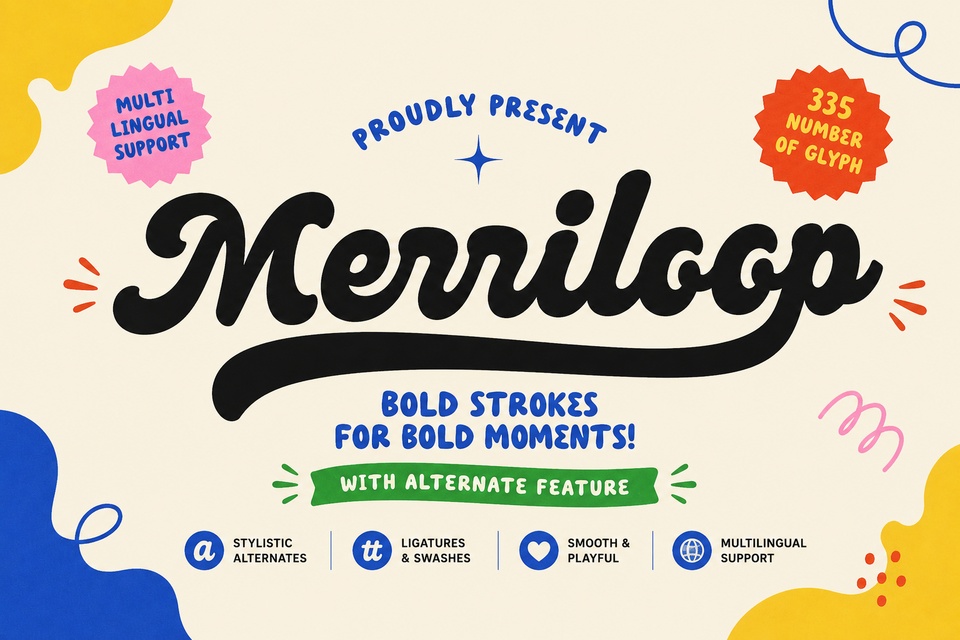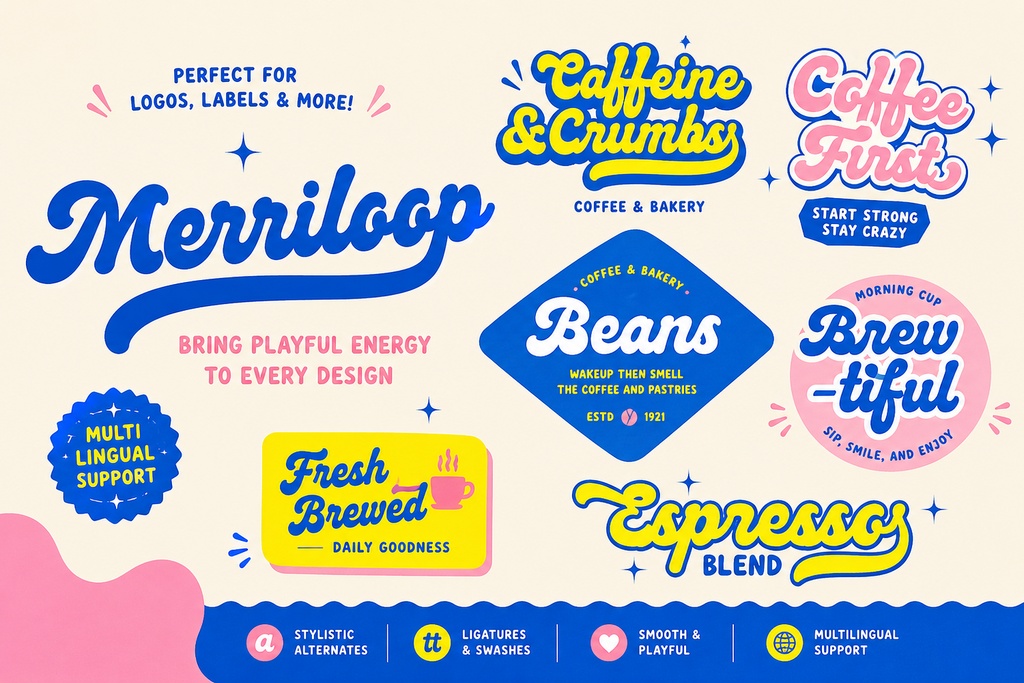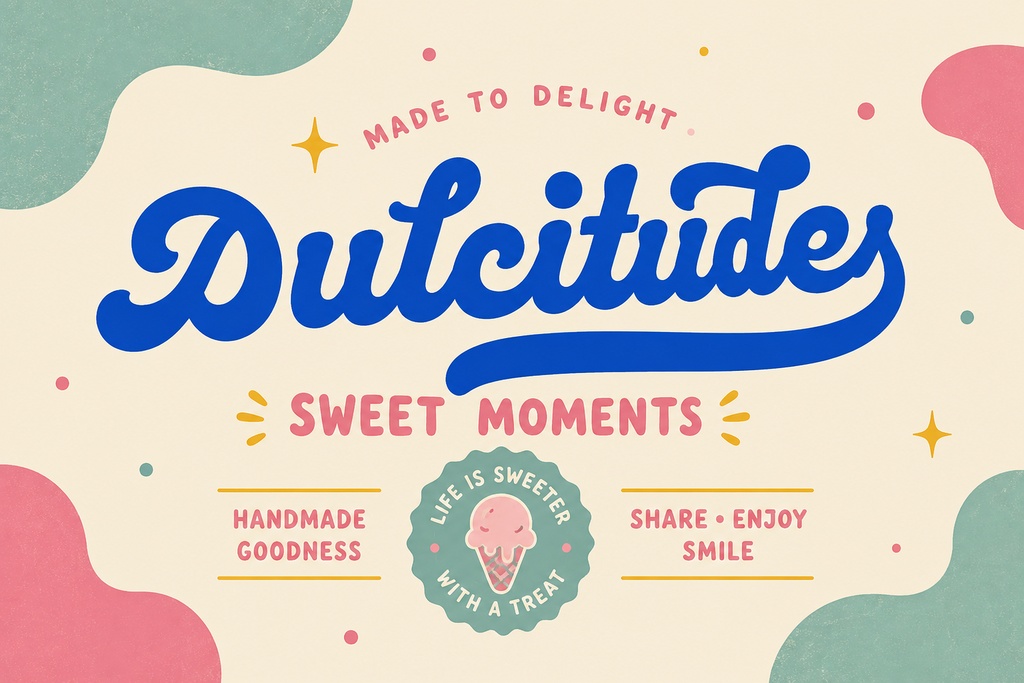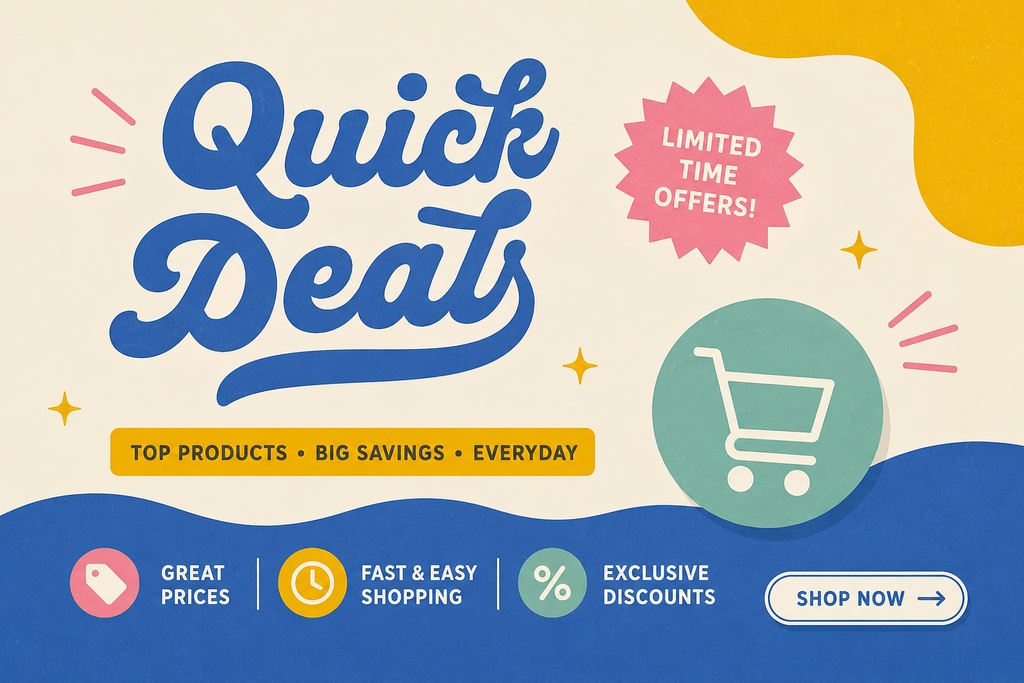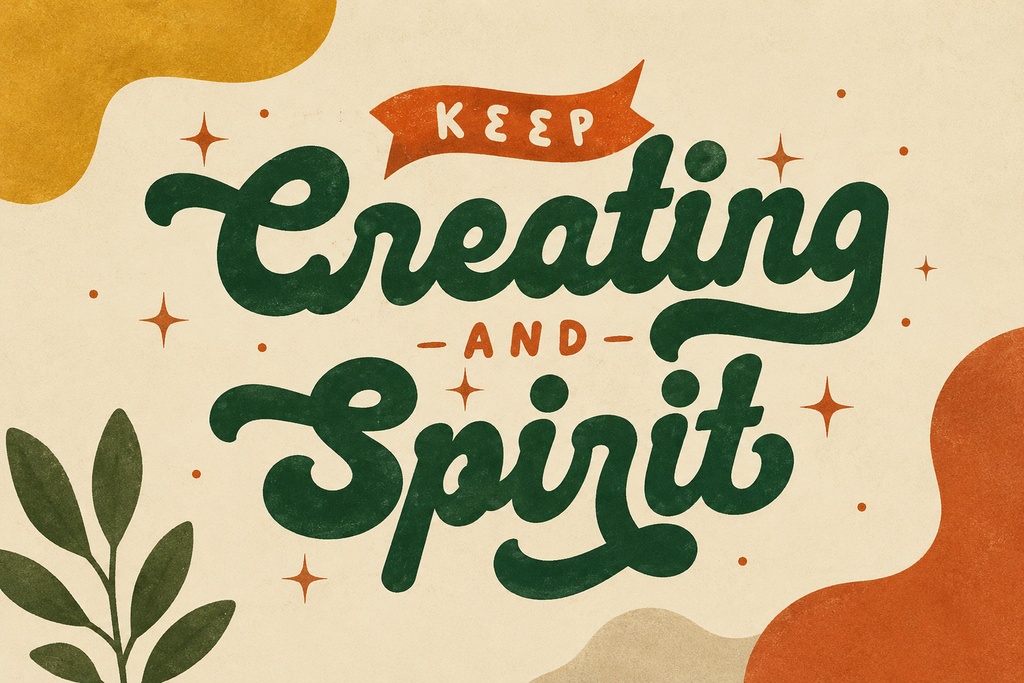
Merriloop — 太字レトロスクリプトフォント
Merriloopは、大胆で丸みを帯びたスクリプト系ディスプレイフォントで、手書き風のレトロスタイルが特徴です。1960年代と1970年代のデザインからインスピレーションを受け、流れるようにつながる文字、表情豊かなカーブやループ、そしてどのサイズでも目を引く太いストロークを備えています。強いビジュアルインパクトが必要な見出し、ポスター、ロゴ、ブランディング、チラシ、その他のデザインに最適です。 フォントにはRegularスタイル1種類が含まれており、305種類の丁寧にデザインされたグリフを収録しています。Basic Latinの大文字・小文字、数字、句読点、記号などが含まれています。 Merriloopには、スタイル代替、3種類のスタイルセット、スワッシュ、リガチャ、カーニングなどのOpenType機能も搭載されています。これらの機能により、対応するデザインアプリケーションのグリフパネルを使用して、別の文字形状を選択したり、装飾的なディテールを追加したり、バランスの取れた文字間隔を維持したりできます。 主な特徴: 大胆で丸みのあるカーブとループ ヴィンテージ感のある太いストローク 3種類のスタイルセット スタイル代替とスワッシュ リガチャとカーニング 305種類のグリフ Basic Latin文字、数字、句読点、記号を収録 OTF、TTF、WOFF、WOFF2ファイル形式対応 Merriloopは、見出し、レトロブランディング、パッケージデザイン、招待状、ソーシャルメディアグラフィック、イベント用チラシ、メニューボード、バッジ、ポスター、Tシャツデザイン、その他のクリエイティブプロジェクトに適しています。 このフォントは、Adobe Illustrator、InDesign、Photoshop、Figma、Canva、Procreate、Affinity、Cricut Design Space、Silhouette Studio、および最新のWebプラットフォームに対応しています。 本製品はCubebrush Commercial Licenseの下で商用利用が許可されています。クレジット表記なしで、クライアント向けプロジェクトや販売用製品に使用できます。 Merriloopをコレクションに加えて、次のデザインに大胆でレトロな個性を与えましょう。